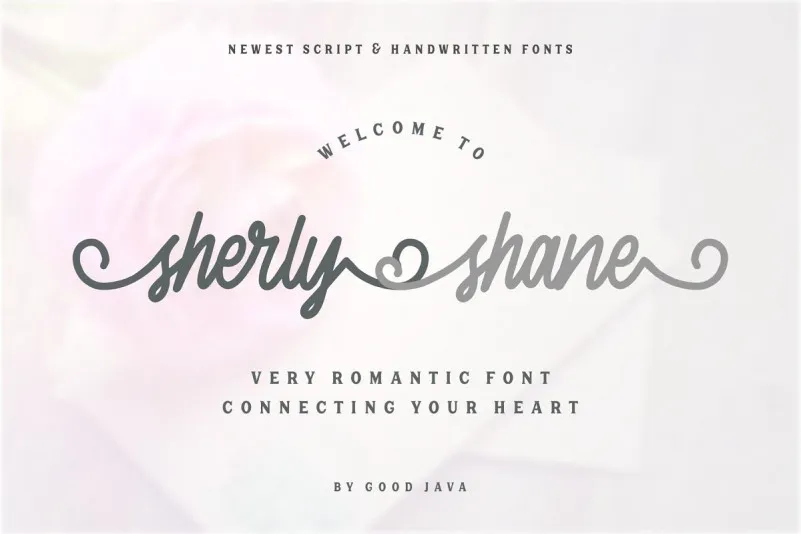
A fonte Sherly Shane Script Font é uma elegante tipografia script que transmite um sentimento natural e handmade. Suas finas curvas e detalhes meticulosamente trabalhados conferem a Sherly Shane um charme único, tornando-a perfeita para qualquer projeto criativo. Este tipo de fonte tem vários swashes no início e final das letras, especialmente nas palavras ao começo e ao fim dos textos. As letras finais são feitas para ligar duas palavras ou letras, o que a torna ainda mais versátil. O conjunto completo desta fonte inclui todas as letras minúsculas com swashes, números e pontuação, além de swashes curtos no início das palavras minúsculas. Sherly Shane é uma fonte romanceada ideal para convites, insígnias, casamentos, moda, marcação, etiquetas ou logotipo. Com sua delicadeza e suavidade, esta font pode transformar qualquer projeto em algo realmente único e destacável. Ideal tanto para designers quanto para aquelas pessoas que querem dar um toque personalizado a seus trabalhos de arte.